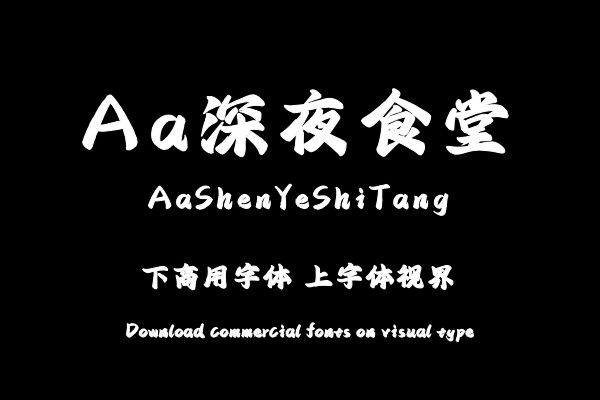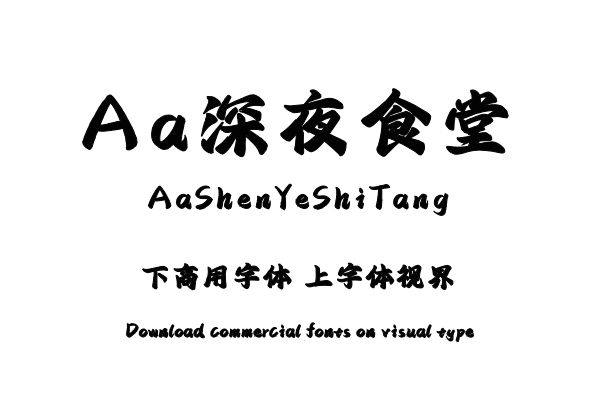
本字体通过漫画感的笔形结合传统书法笔法形成风格独特的手书风格,通过口等封闭结构上宽下窄的倒梯形结构和外扩的中宫形成上大下小的字形感受,视觉感受轻松可爱,萌感稚气......购买须知:“下载服务费”与“字体VIP”所获得字体 仅用于个人非商用, 商用请联系付费授权。本字体为电脑用字,手机没有root权限不支持直接手机换字(手机如何root,请自行百度搜索教程)。购买前请先 了解清楚后再付款 ,字体为虚拟产品无法回收 一旦购买不支持退款。